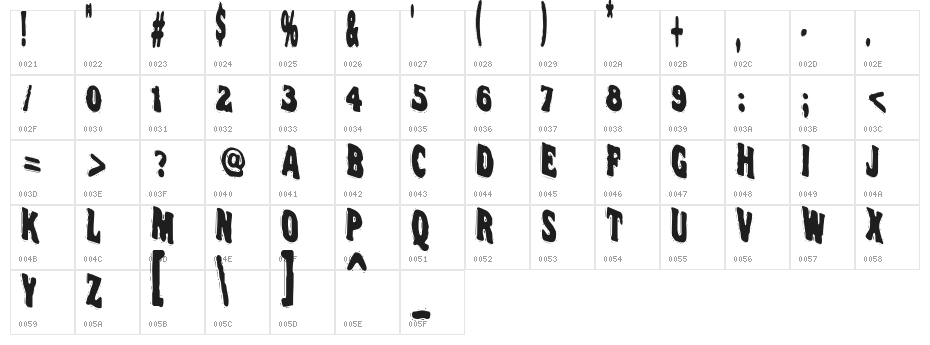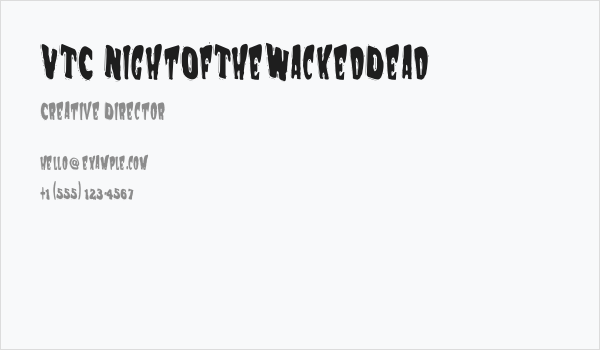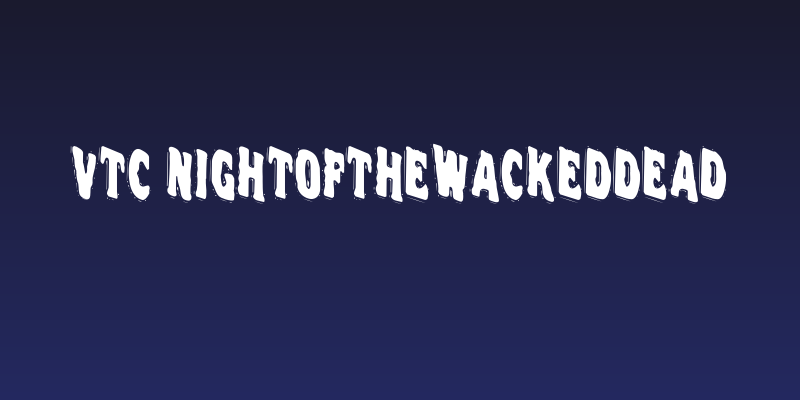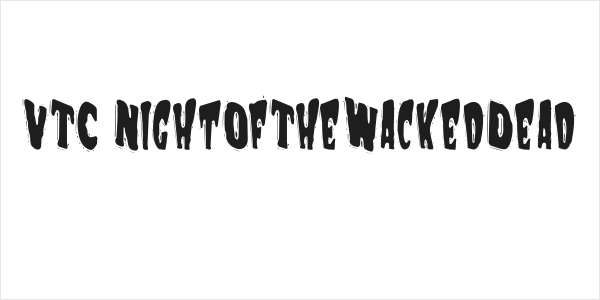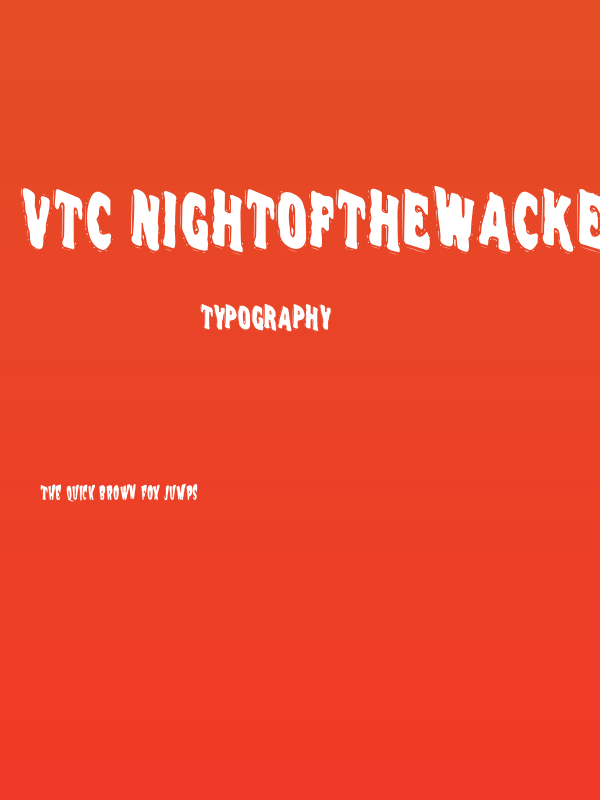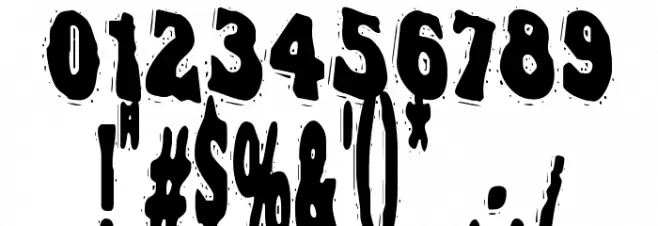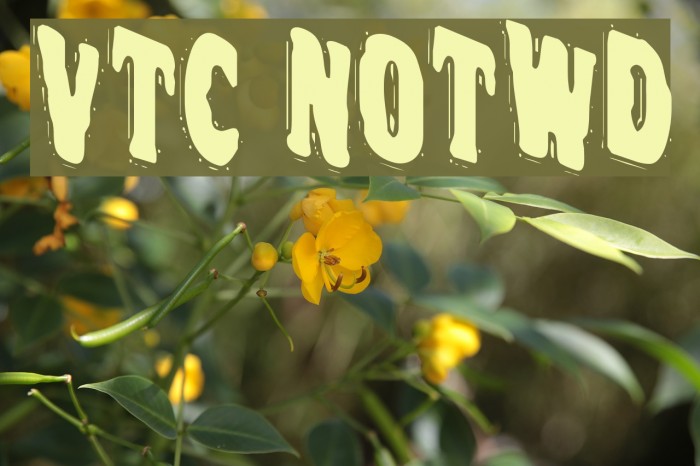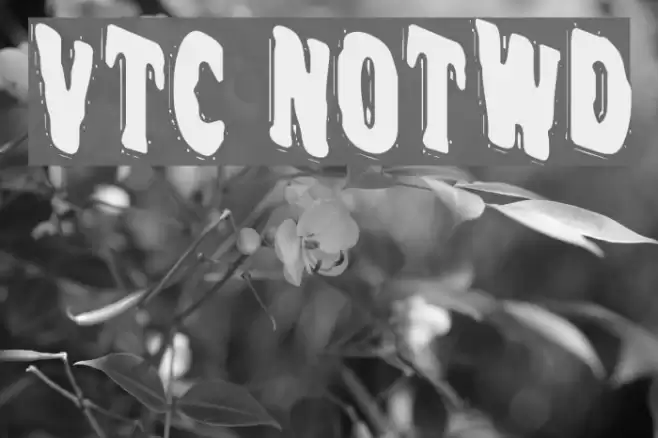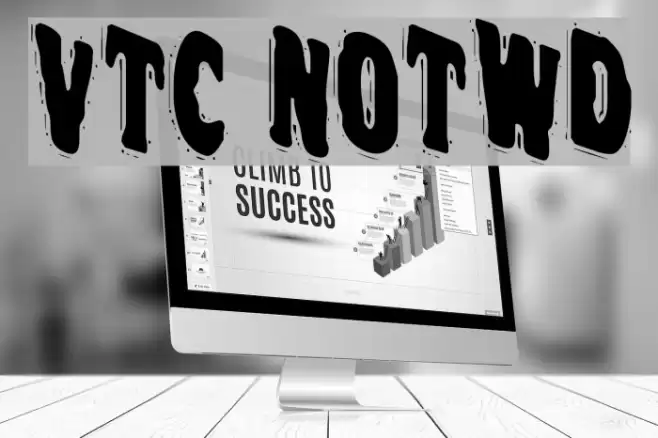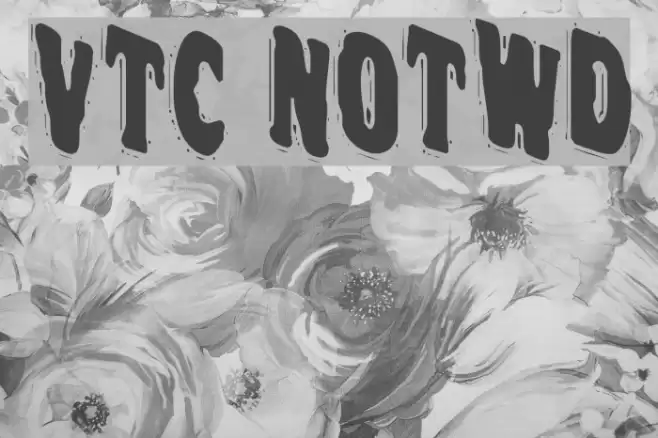
VTC NightOfTheWackedDead Font
| Projets proposés | Ideal for Halloween designs, horror movie posters, themed party invitations, and spooky event branding. |
VTC NightOfTheWackedDead